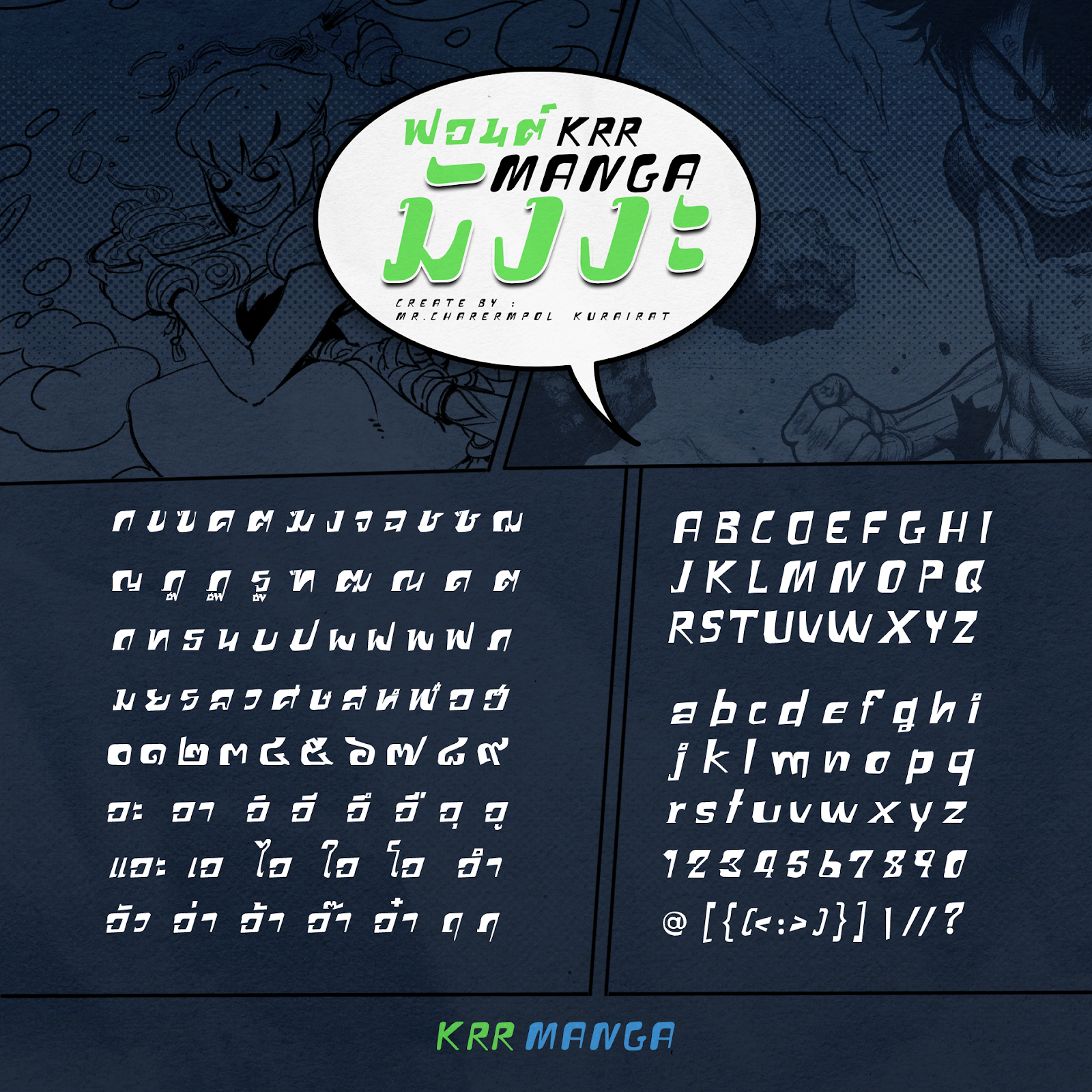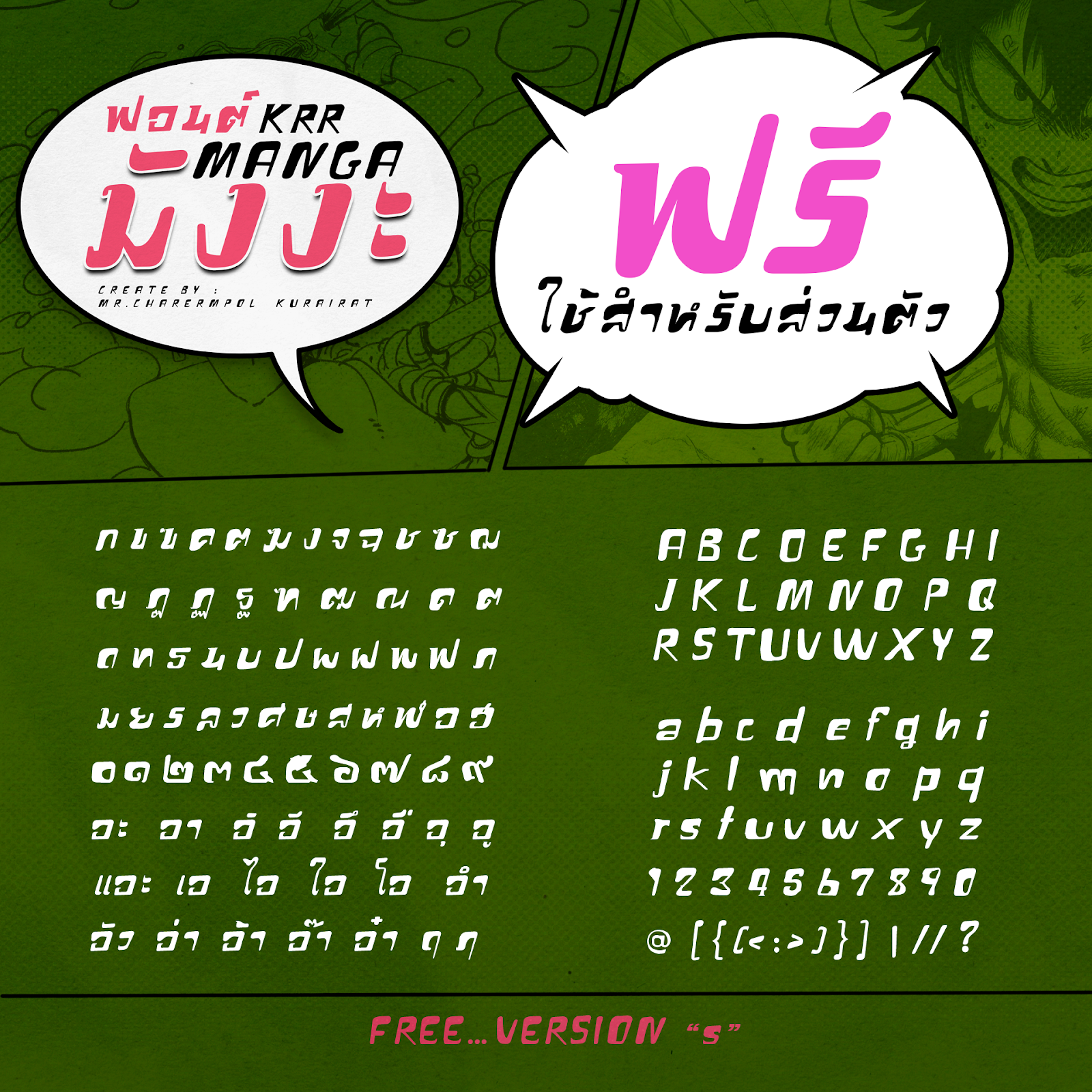
KRR MANGA (เค อาร์ อาร์ มังงะ)
ฟอนต์  KRR MANGA  ( เค อาร์ อาร์ มังงะ)
เป็นอีกฟอนต์ในสายงาน คนเขียนการ์ตูน ใช้เป็นตัวเอฟเฟค
ที่อยากนำเสนอมากๆ
เป็นเวอร์ชั่น ที่ยังไม่สมบูรณ์เต็มร้อยนะครับ แต่พอใช้ได้